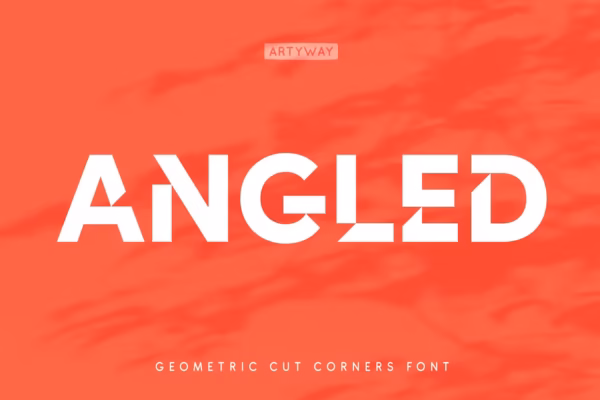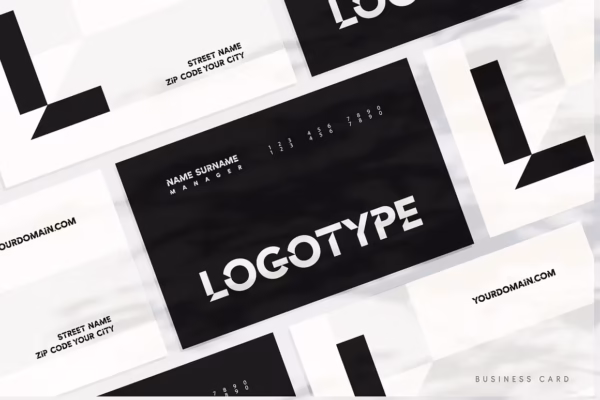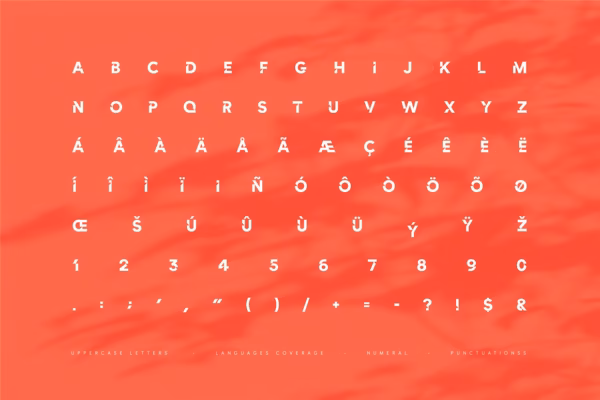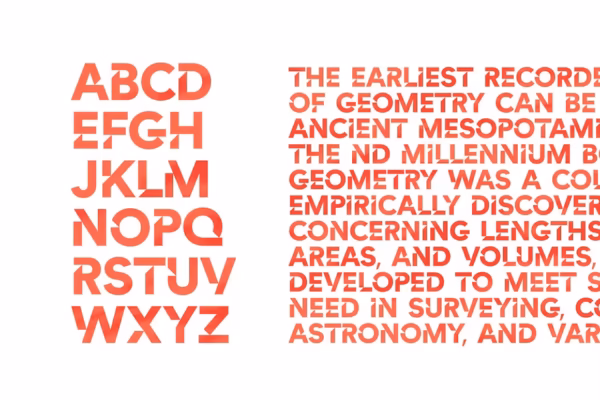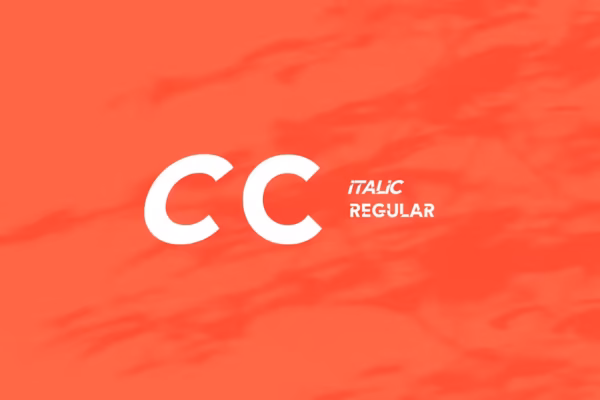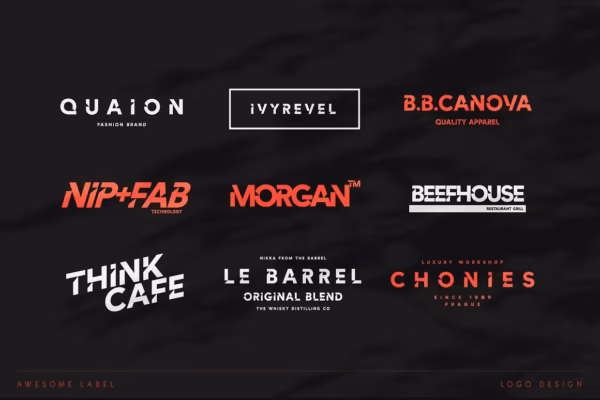
این فونت ضخیم و مدرن با الهام از جدیدترین ترندهای تایپوگرافی تیتر برای طراحیهای دیجیتال ساخته شده است. برشهای هندسی دقیق و ظاهر منحصربهفرد آن، جلوهای حرفهای و آیندهنگر به نوشتههای شما میبخشد.
این فونت انتخابی ایدهآل برای طراحیهای آیندهنگر، گیمینگ، رابطهای کاربری GUI، رابطهای HUD، پوسترها، کاورهای دیجیتال و سایر پروژههای گرافیکی مدرن است.